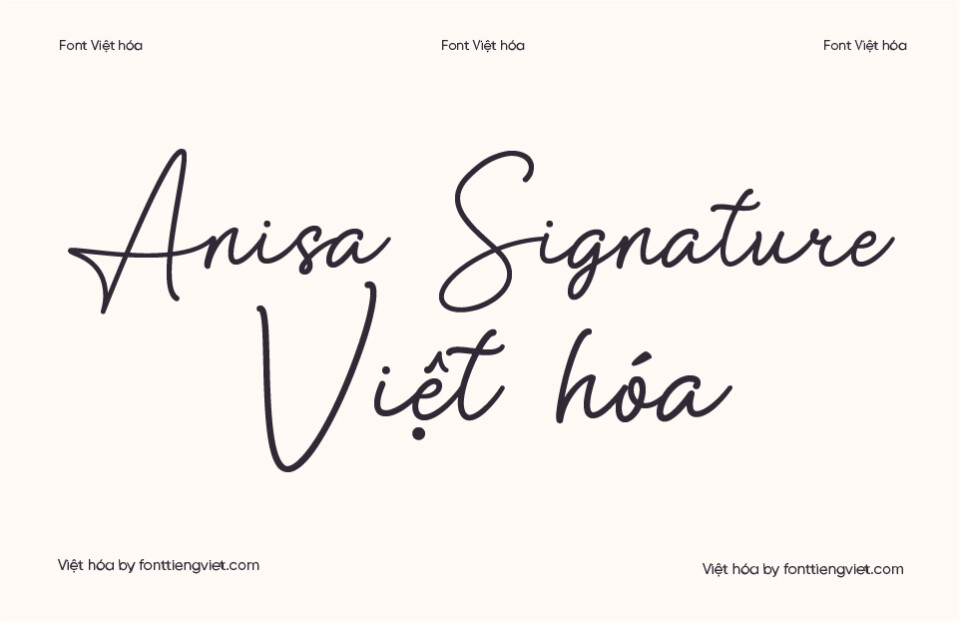
Tuyệt Phẩm Font Việt hóa 1FTV VIP Anisa Signature: Khám Phá Nét Chữ Ký Sang Trọng Cho Thiết Kế
Trong thế giới thiết kế đồ họa và typography, việc sở hữu một bộ Font Chữ độc đáo và chất lượng là yếu tố then chốt tạo nên sự khác biệt cho dự án. Đặc biệt, đối với các bạn học sinh, sinh viên hay những nhà thiết kế đang tìm kiếm sự tinh tế, sang trọng cho các ấn phẩm học thuật hoặc portfolio, sự xuất hiện của Font Việt hóa 1FTV VIP Anisa Signature chính là một bước đột phá. Đây không chỉ là một phông chữ; nó là tuyên ngôn về phong cách và đẳng cấp. Phông chữ Anisa Signature nổi tiếng với nét viết tay mềm mại, chân thực, mô phỏng hoàn hảo chữ ký của một người chuyên nghiệp, và phiên bản Việt hóa này đã mở rộng khả năng sử dụng của nó cho cộng đồng thiết kế Việt Nam.
Phiên bản VIP này đảm bảo rằng mọi ký tự, dấu câu, và đặc biệt là các dấu tiếng Việt đều được chăm chút tỉ mỉ, giúp bạn tạo ra những tác phẩm có tính thẩm mỹ cao mà không gặp bất kỳ lỗi font nào. Hãy cùng khám phá lý do tại sao bộ font này lại trở thành lựa chọn hàng đầu cho các dự án quan trọng, từ thiết kế thiệp mời tốt nghiệp đến các bài thuyết trình khoa học cấp cao.
Tại Sao Font Việt hóa 1FTV VIP Anisa Signature Lại Quan Trọng Với Người Thiết Kế?
Sự quan trọng của một phông chữ chữ ký nằm ở khả năng truyền tải cảm xúc và cá tính. Anisa Signature làm được điều đó một cách xuất sắc. Được xây dựng dựa trên phong cách viết tay calligraphy hiện đại, font này mang lại cảm giác cá nhân hóa mạnh mẽ, rất phù hợp khi cần mô phỏng chữ ký của giáo viên, hiệu trưởng trên bằng cấp, hoặc tạo điểm nhấn độc quyền cho thương hiệu cá nhân của học sinh, sinh viên khởi nghiệp. Khác biệt lớn nhất của phiên bản Việt hóa 1FTV VIP chính là chất lượng xử lý dấu tiếng Việt. Thông thường, các font chữ nước ngoài khi được chuyển ngữ thường gặp vấn đề về kerning (khoảng cách giữa các ký tự) và vị trí của dấu. Với phiên bản VIP này, mọi lỗi nhỏ đều được khắc phục triệt để, đảm bảo tính thẩm mỹ và chuyên nghiệp tuyệt đối.
Việc đầu tư vào một bộ font chất lượng như Anisa Signature VIP thể hiện sự tôn trọng đối với người xem và sự nghiêm túc trong công việc. Đối với các bạn chuẩn bị cho kỳ thi tốt nghiệp hoặc các dự án cuối khóa, việc trình bày đẹp mắt bằng một font chữ độc đáo có thể tạo ấn tượng mạnh mẽ, giúp bài làm nổi bật giữa hàng trăm bài khác.
Đặc Điểm Nổi Bật Của Anisa Signature
Font Anisa Signature được thiết kế với nhiều biến thể (alternates) và nét nối (ligatures) phong phú, cho phép người dùng tùy chỉnh chữ viết sao cho tự nhiên và đa dạng nhất. Sự linh hoạt này là chìa khóa để tránh sự lặp lại đơn điệu thường thấy ở các font chữ ký thông thường. Dưới đây là những điểm mạnh cốt lõi:
- Tính Việt hóa Cao Cấp: Hỗ trợ đầy đủ bộ ký tự Latin mở rộng và hệ thống dấu tiếng Việt chuẩn xác (ă, â, đ, ê, ô, ơ, ư).
- Phong Cách Chữ Ký Tự Nhiên: Mô phỏng đường nét mực viết tay mềm mại, tốc độ, tạo cảm giác như được viết trực tiếp bằng bút lông hoặc bút thư pháp.
- Sự Sang Trọng (VIP Status): Thường được sử dụng trong các ấn phẩm cao cấp như thiệp cưới, logo thương hiệu xa xỉ, và các tài liệu chứng nhận quan trọng.
Ứng Dụng Đa Dạng Trong Học Tập và Đồ Họa
Đối với cộng đồng học sinh, sinh viên, và giáo viên, Font Việt hóa 1FTV VIP Anisa Signature mang lại nhiều lợi ích thiết thực không chỉ trong lĩnh vực thiết kế mà còn trong các hoạt động học thuật. Từ việc tạo tiêu đề nổi bật cho bài nghiên cứu khoa học cho đến việc thiết kế bìa sách, bìa báo cáo, font chữ này đều phát huy tối đa hiệu quả. Việc sử dụng font chữ ký trong các tài liệu liên quan đến thi cử hoặc đánh giá cuối kỳ giúp tài liệu đó mang tính cá nhân hóa và chuyên nghiệp hơn rất nhiều. Ví dụ, một sinh viên có thể sử dụng font này để thiết kế signature cho email học thuật hoặc tạo watermark độc quyền cho các tài liệu chia sẻ.
Ngoài ra, font chữ này còn rất hữu ích cho các dự án liên quan đến trường học, chẳng hạn như thiết kế áo lớp, kỷ yếu tốt nghiệp, hay các banner quảng bá sự kiện của trường. Sự kết hợp giữa nét truyền thống của chữ viết tay và sự hiện đại trong thiết kế tạo ra một hiệu ứng thị giác độc đáo, thu hút người nhìn ngay từ cái chạm mắt đầu tiên. Đây là một công cụ mạnh mẽ giúp các bạn trẻ thể hiện sự sáng tạo và năng lực thiết kế của mình, một lợi thế lớn trong thị trường lao động ngày càng cạnh tranh.
Nâng Tầm Typography Việt Với Bản Việt Hóa Chuyên Sâu
Nền tảng thành công của bất kỳ font chữ Việt hóa nào nằm ở khả năng xử lý các dấu phụ (diacritics) phức tạp của tiếng Việt. Phiên bản VIP Anisa Signature được các chuyên gia typography kiểm duyệt kỹ lưỡng, đảm bảo rằng dấu sắc, huyền, hỏi, ngã, nặng được đặt đúng vị trí, không bị chồng chéo hay quá xa ký tự gốc. Điều này đặc biệt quan trọng khi làm việc với kích thước chữ nhỏ hoặc in ấn chất lượng cao. Kerning đã được điều chỉnh thủ công cho hàng trăm cặp ký tự, giúp dòng chữ chảy mượt mà và dễ đọc, tránh cảm giác bị gián đoạn. Đây là điểm khác biệt lớn so với các phiên bản font miễn phí, không chuyên nghiệp tràn lan trên mạng, thường xuyên gây ra lỗi font khiến tài liệu bị mất đi tính nghiêm túc.
Nếu bạn đang chuẩn bị cho một bài thuyết trình quan trọng, một luận văn thạc sĩ hay chỉ đơn giản là cần một chữ ký điện tử có đẳng cấp, việc lựa chọn font 1FTV VIP Anisa Signature là một quyết định đầu tư thông minh. Chất lượng là yếu tố không thể thay thế, và font này chính là minh chứng rõ ràng nhất cho điều đó, hỗ trợ đắc lực cho mọi nhu cầu thiết kế đồ họa từ cơ bản đến nâng cao.
Tóm lại, Font Việt hóa 1FTV VIP Anisa Signature không chỉ đơn thuần là một bộ ký tự đẹp mắt; nó là biểu tượng của sự chuyên nghiệp, tinh tế, và đẳng cấp. Với chất lượng Việt hóa hoàn hảo, nét chữ ký độc đáo, và khả năng ứng dụng rộng rãi từ các dự án học đường đến thương hiệu cá nhân, đây chắc chắn là một tài sản không thể thiếu trong bộ sưu tập của mọi nhà thiết kế, học sinh, và người làm nội dung. Việc sử dụng Font Chữ chất lượng cao như Anisa Signature sẽ giúp bạn nâng tầm giá trị thẩm mỹ của sản phẩm, để lại ấn tượng sâu sắc và bền vững. Hãy khám phá ngay sức mạnh của phông chữ này để biến những ý tưởng sáng tạo của bạn thành hiện thực một cách hoàn hảo nhất.